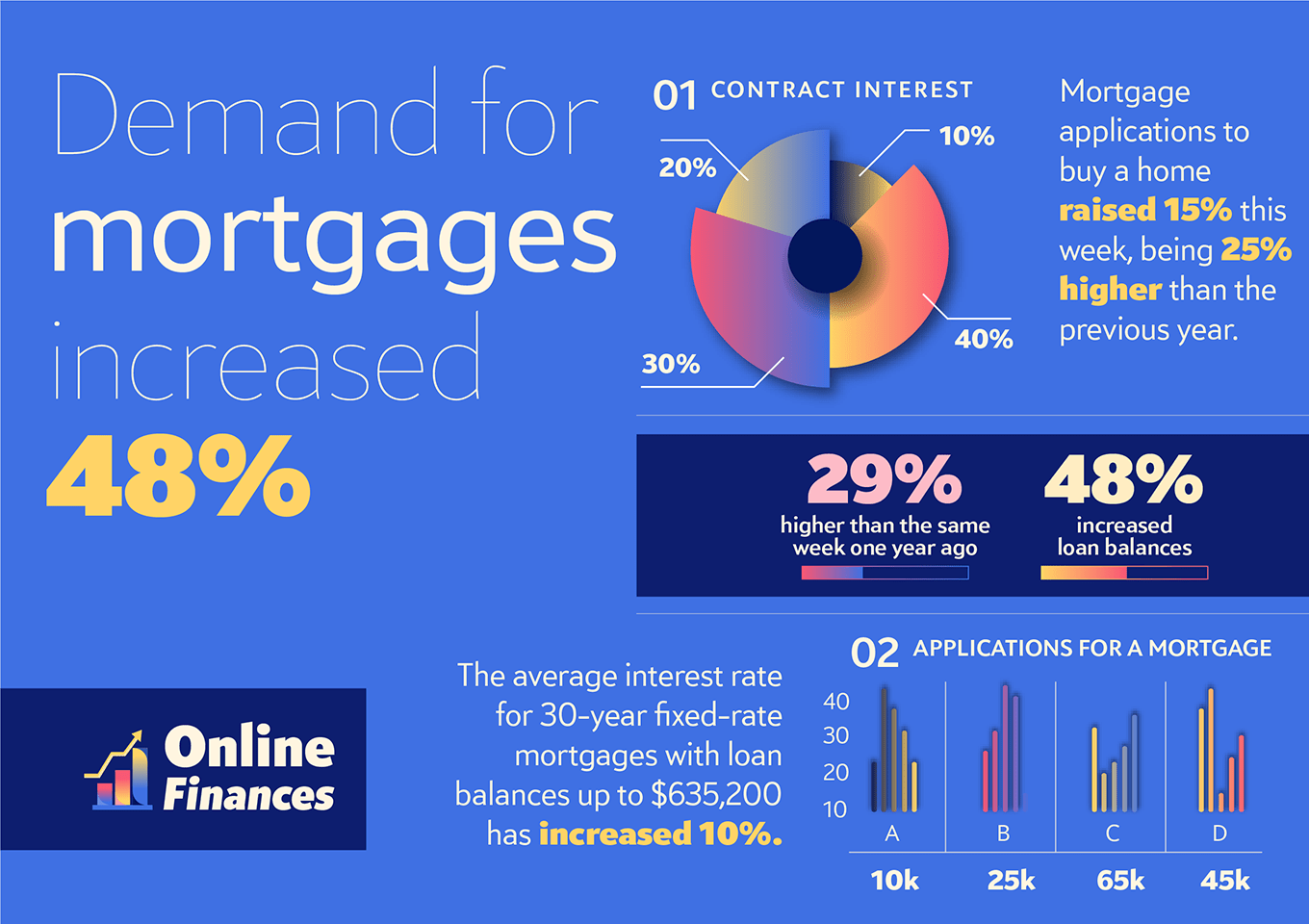
クリーンで明るい印象のサンセリフ体です。やや長めに設計されたアセンダー・ディセンダーラインが上品な印象を与える一方で、大文字のレッグや小文字のステムに見られる斜めカットが組版に心地よいリズムを演出するユニークな書体です。細いウエイトは文章組に、カットの表情が色濃くなる太いウエイトは見出しでの利用に最適です。